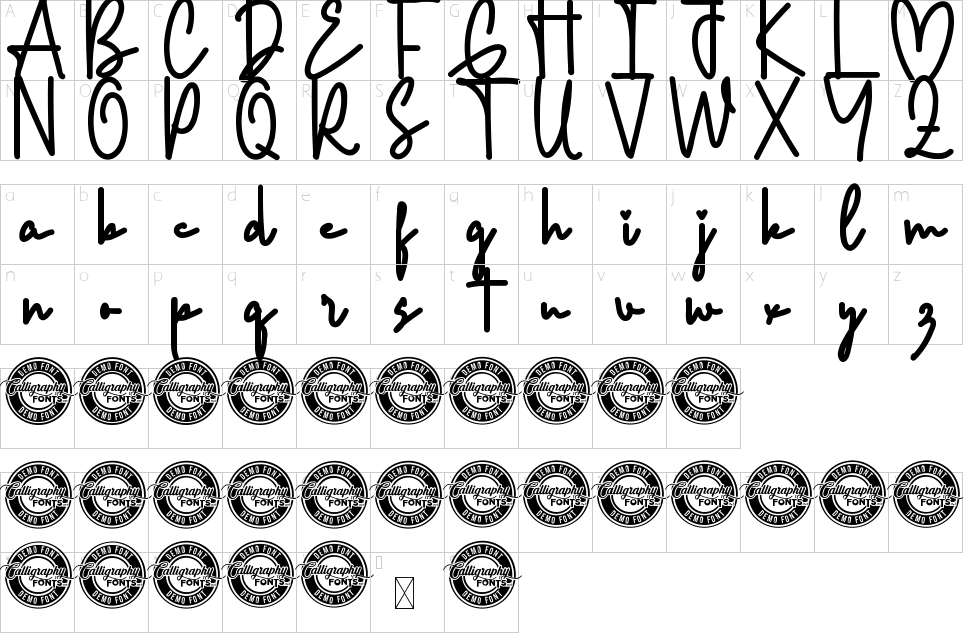
A fonte Good Memories oferece um leque de opções para quem busca uma fonte grata e delicada para seu próximo projeto de design. Com sua elegância, a Good Memories é perfeita para criar designs que lembram aqueles momentos especiais da sua memória. Desenvolvida pela incrível equipe de CalligraphyFonts, a Good Memories tem sido popular entre os designers e desenvolvedores de software por seu charme e versatilidade. Para designers que valorizam a simplicidade e a delicadeza, a Good Memories é uma ótima escolha para criar designs memoráveis e cheios de bom gosto. Esta fonte já foi baixada mais de 3.156 vezes, testemunhando seu valor e popularidade. Não perca a oportunidade de adquirir esta fonte de qualidade para seus projetos em desenvolvimento.